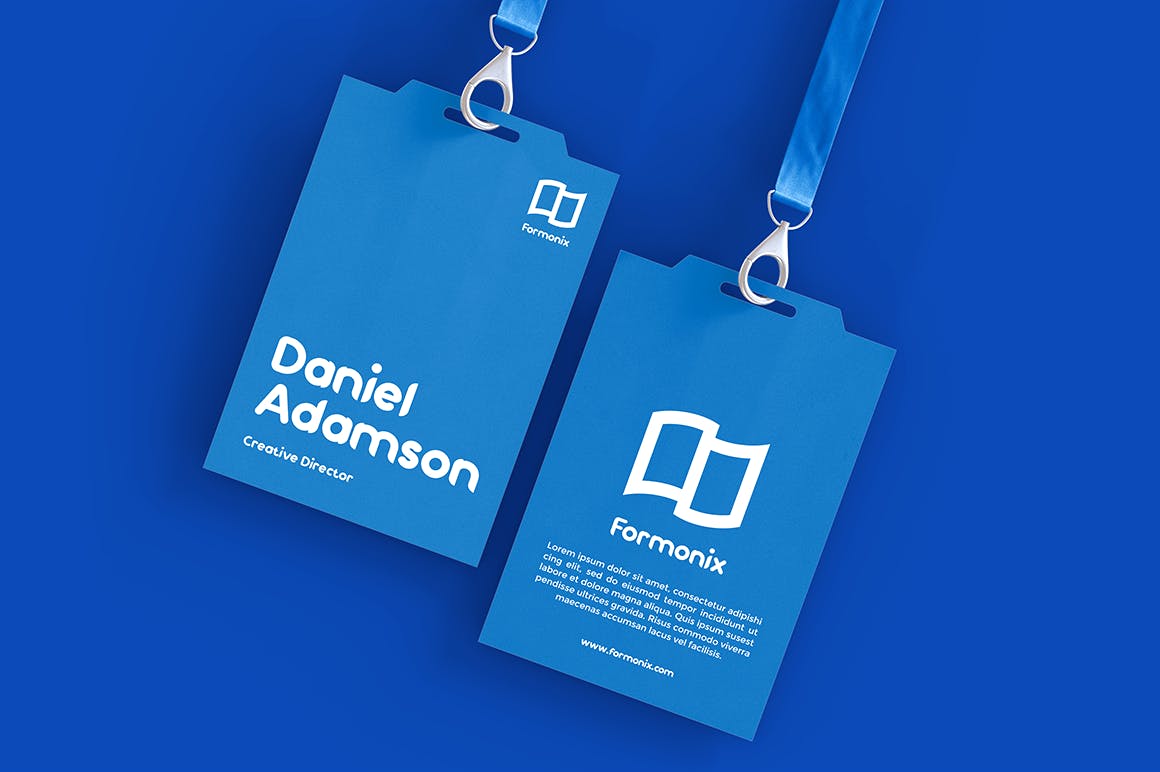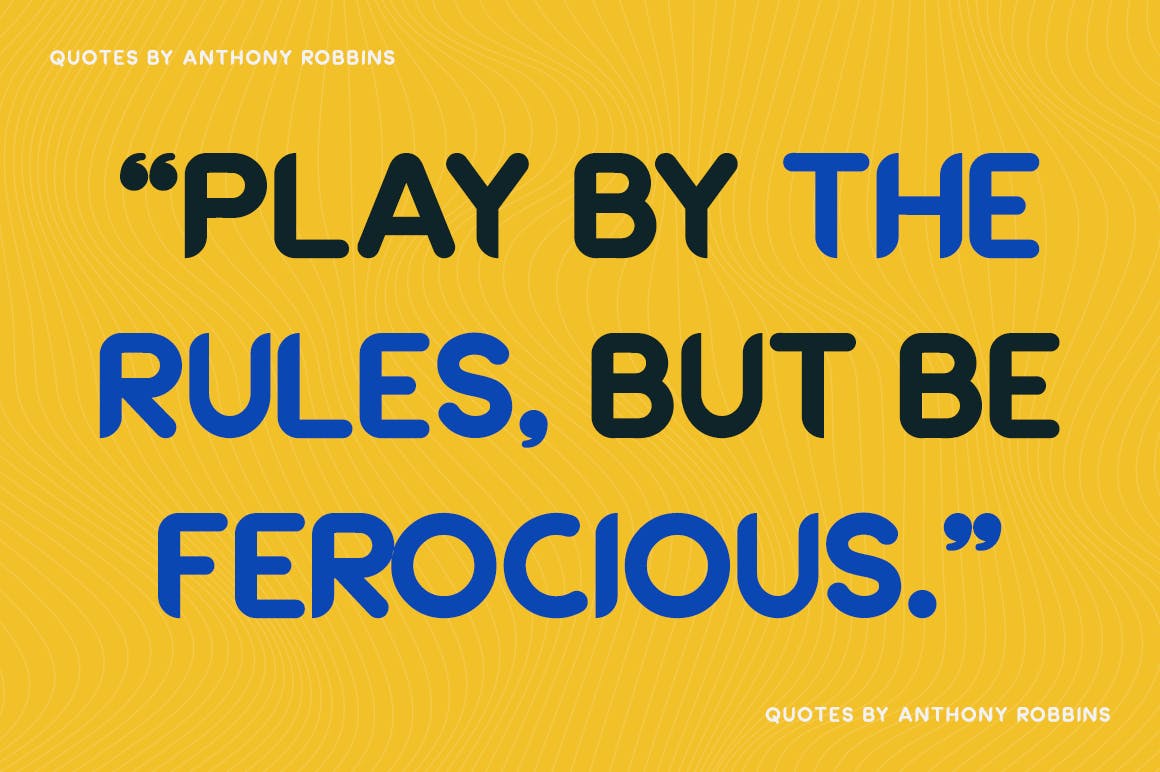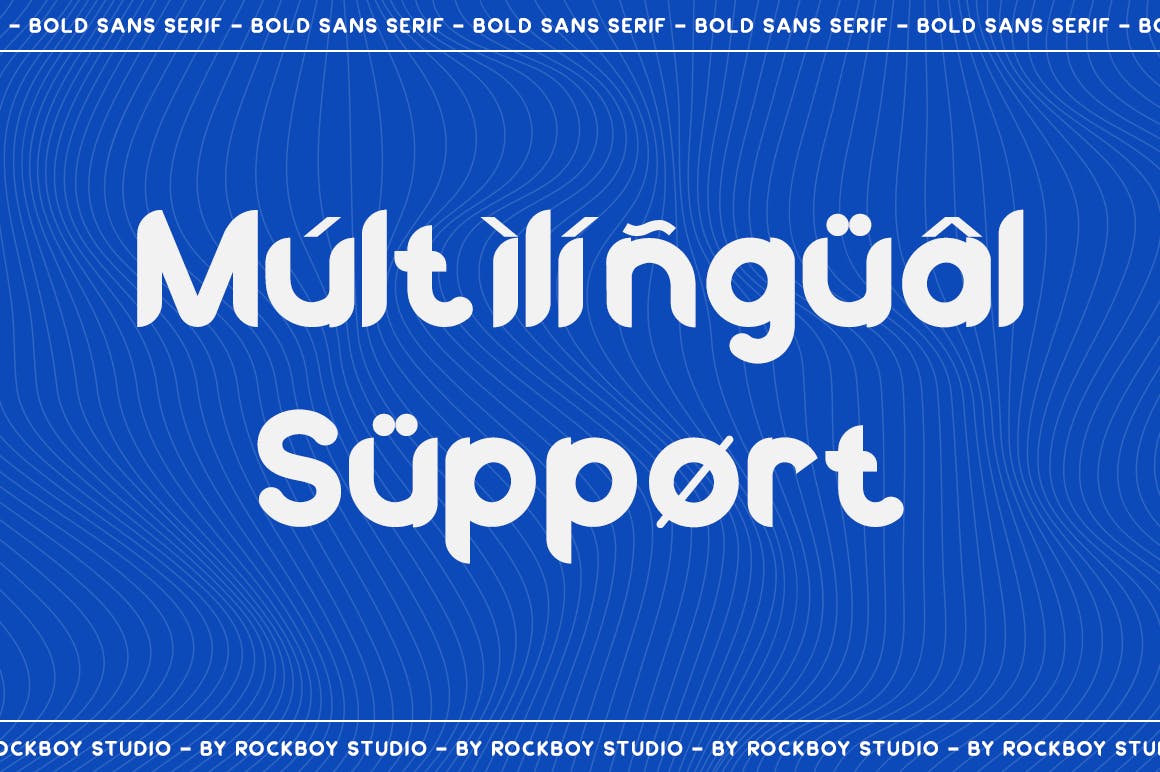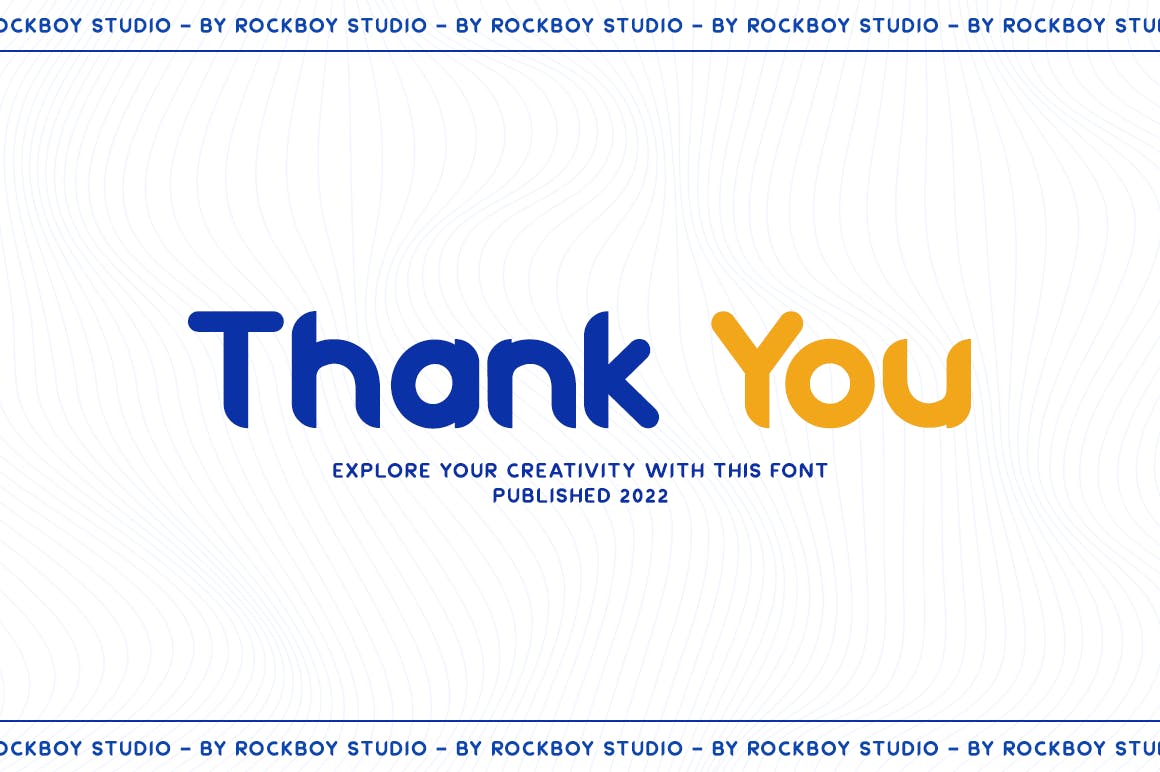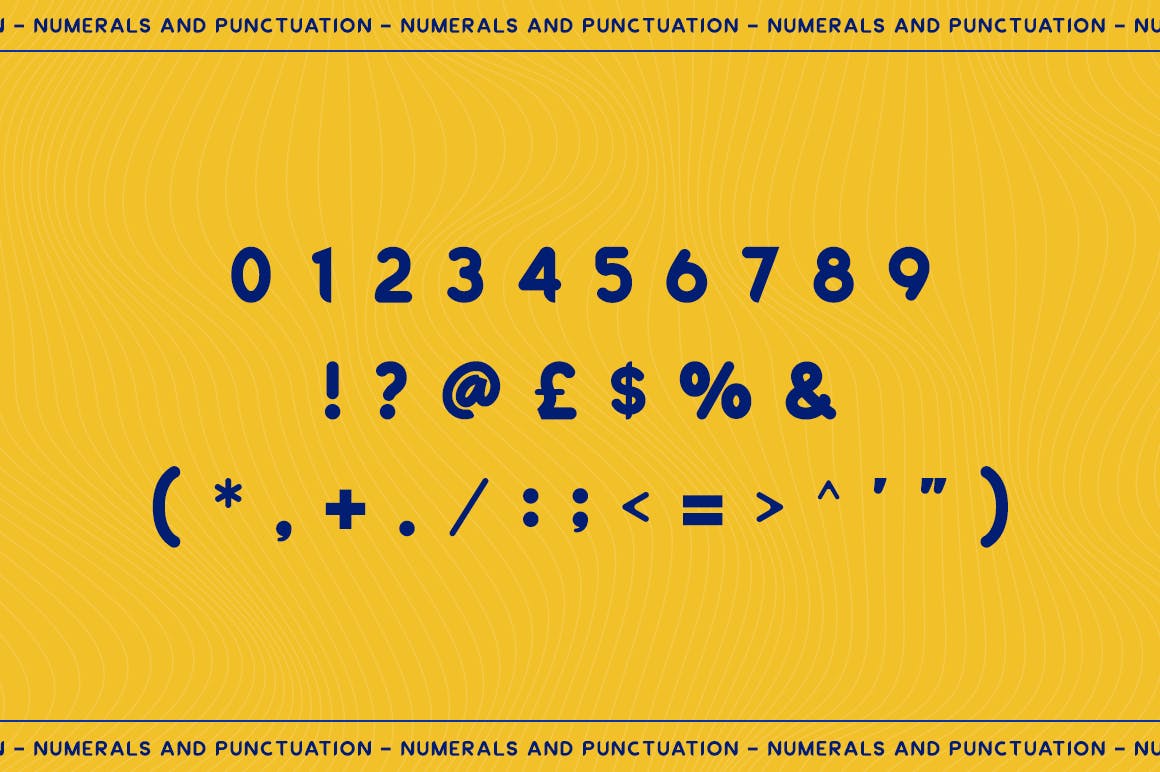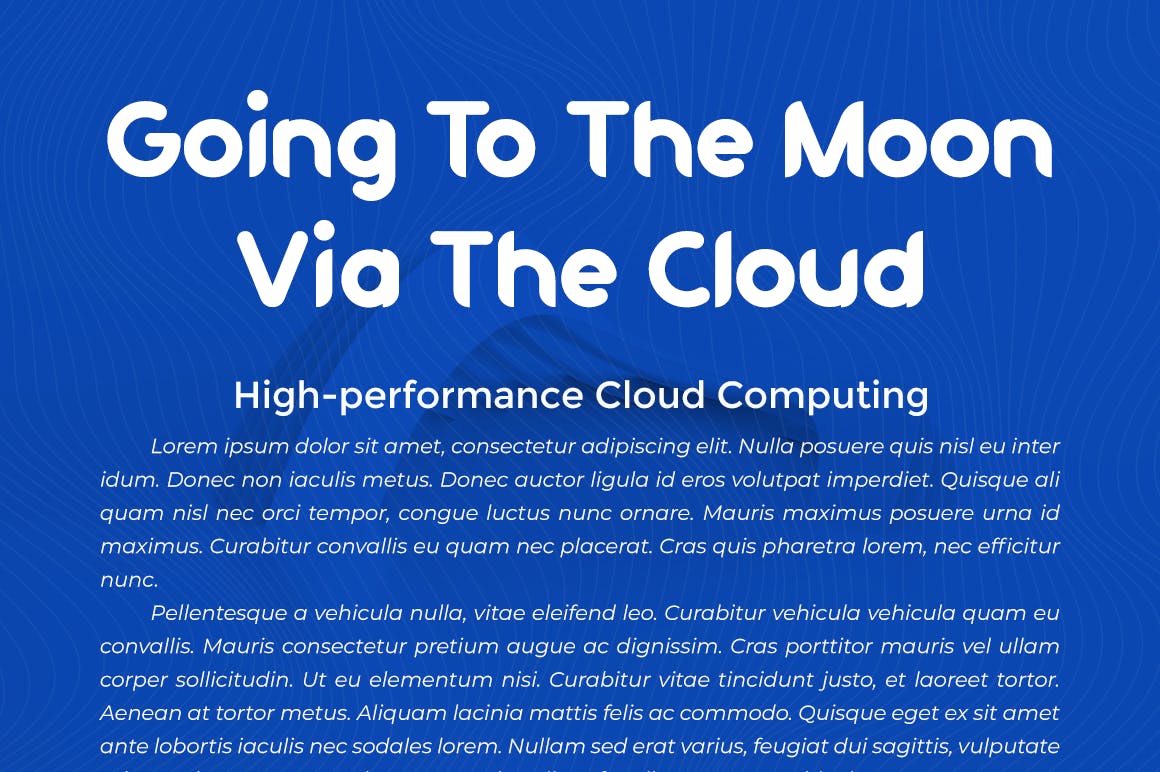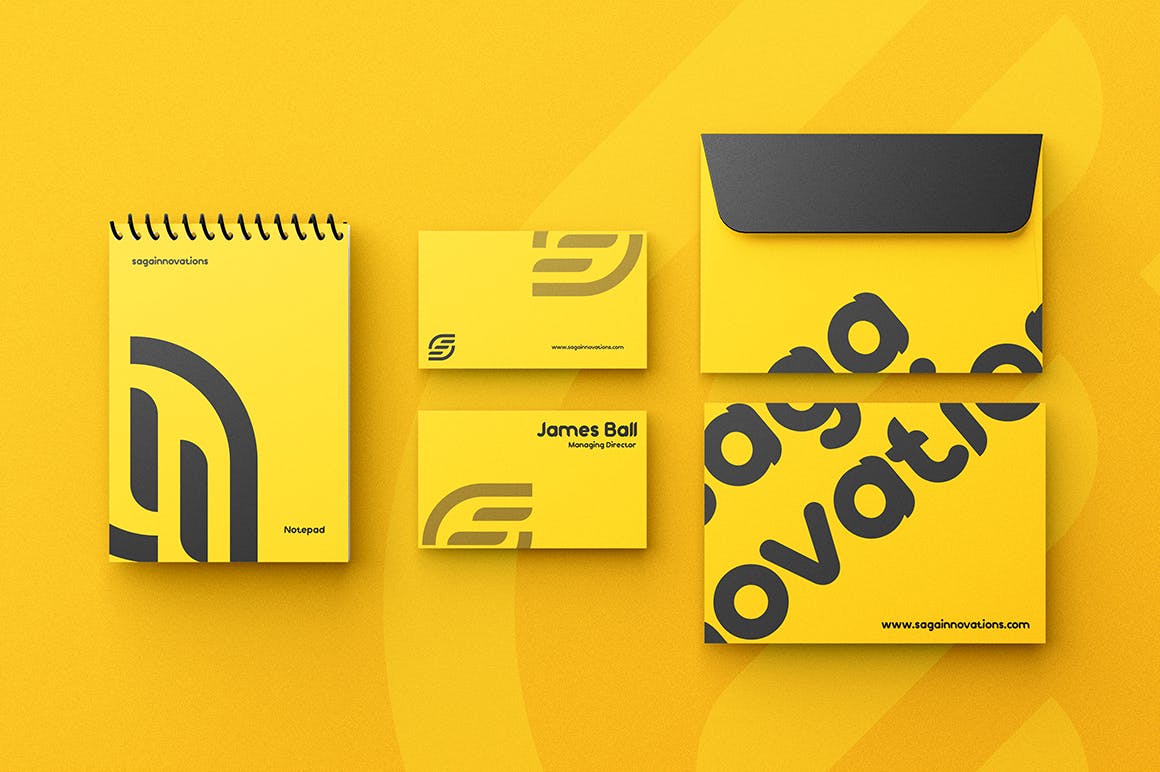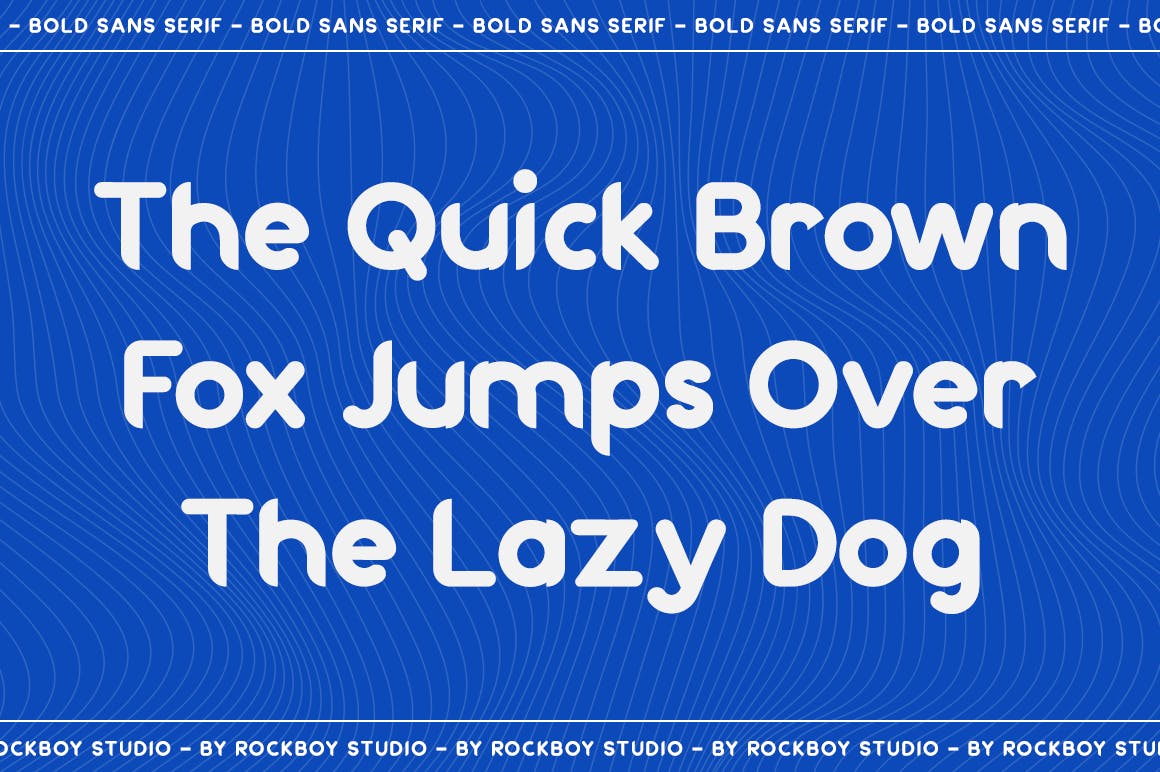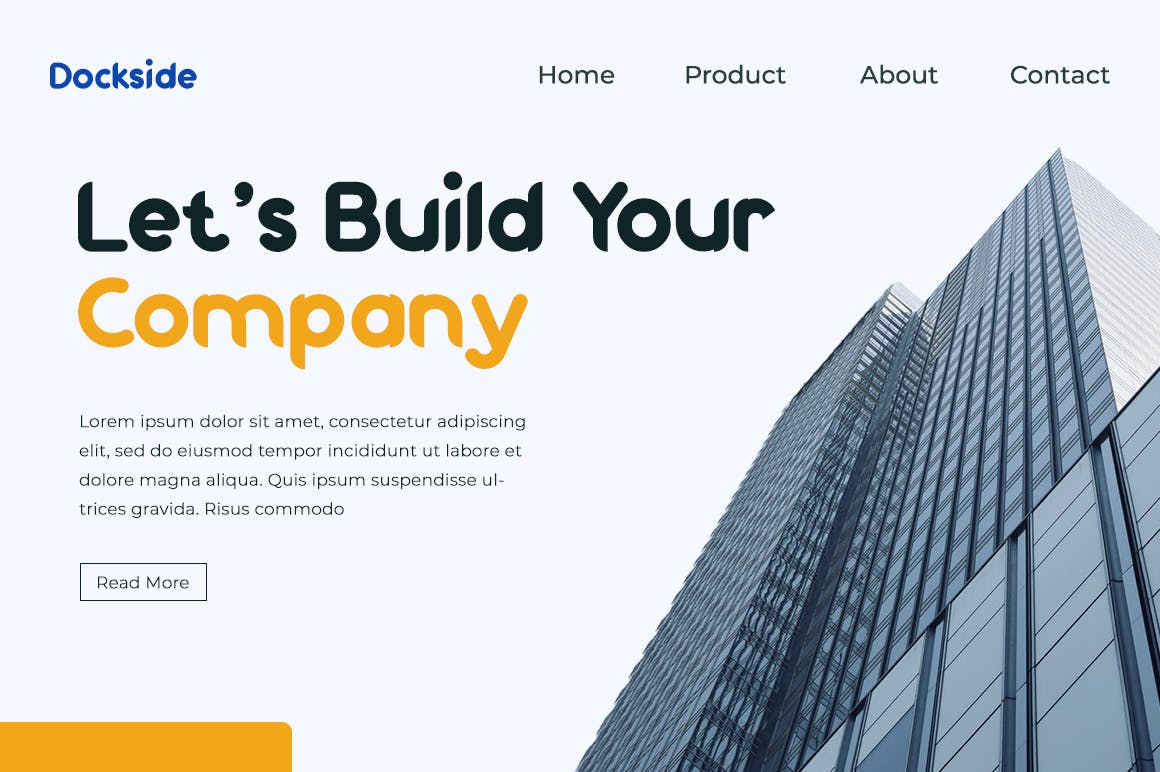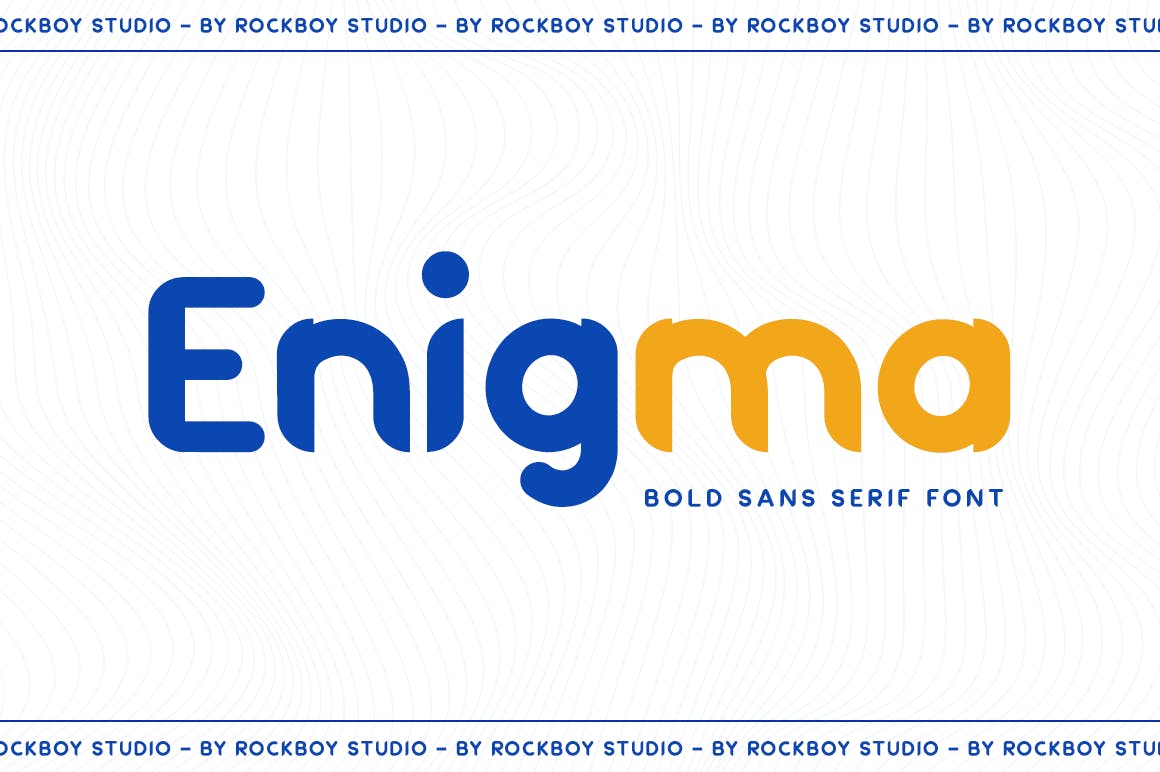
Enigma یک فونت سانس سریف زیبا و شیک است که میتواند ایدههای خلاقانه شما را ارتقا دهد. از کارتها تا برندینگ، برچسبها و بسیاری دیگر، این فونت به هر پروژهای که در نظر دارید، جلوهای خاص میبخشد!